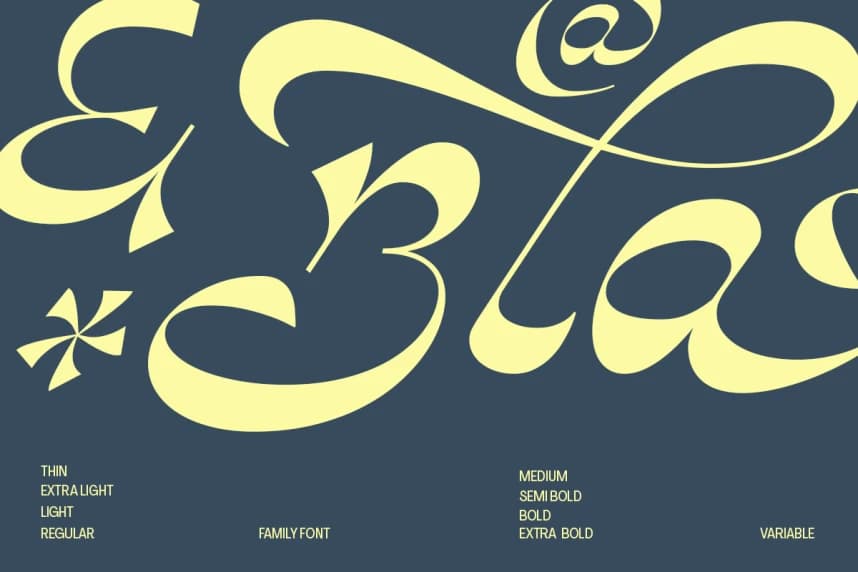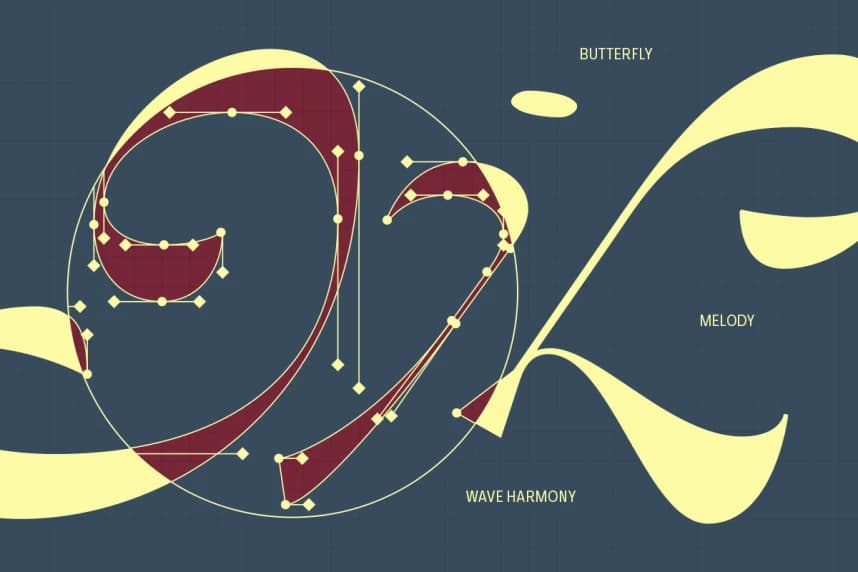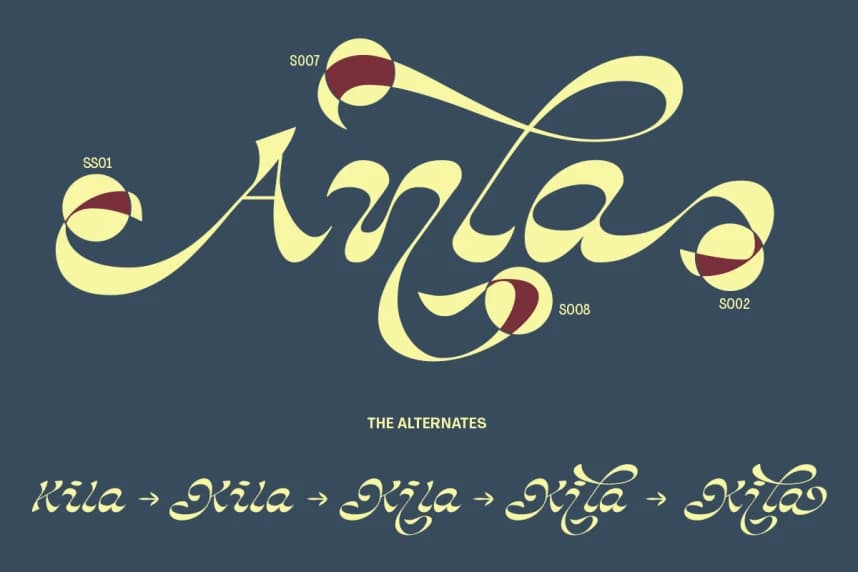
Dh Joleta Font
Dh Joleta Font, yumuşak kadınsı zarafetten, akıcı kelebek kanatlarından ve zarif sanatsal kaligrafiden esinlenen el yapımı bir lüks güzellik yazı tipi ailesidir. Zarif eğriler, ifade dolu swash'lar ve rafine yüksek kontrastlı hatlar ile tasarlanmıştır.
Dh Joleta Font, yumuşak kadınsılıktan, akıcı kelebek kanatlarından ve zarif sanatsal kaligrafiden ilham alan el yapımı lüks güzellik yazı tipi ailesidir. İncelikli eğriler, ifade dolu süslemeler ve belirgin yüksek kontrastlı hatlar ile tasarlanmıştır.